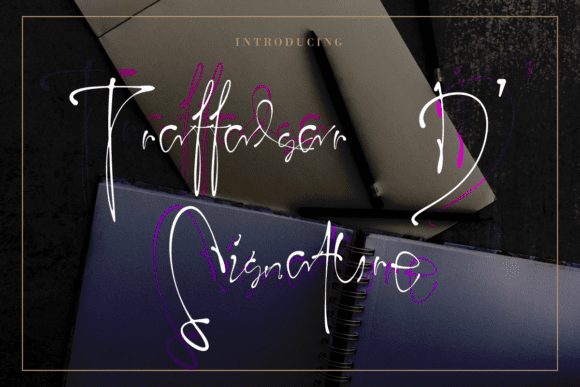
Название: Trafalgar D’ Signature Font
Trafalgar D' Signature - это элегантная рукописная подпись с невероятно естественным стилем.
Это идеальный шрифт для придания индивидуального шарма широкому спектру дизайнерских идей!
Название: Trafalgar D’ Signature Font
Trafalgar D' Signature - это элегантная рукописная подпись с невероятно естественным стилем.
Это идеальный шрифт для придания индивидуального шарма широкому спектру дизайнерских идей!